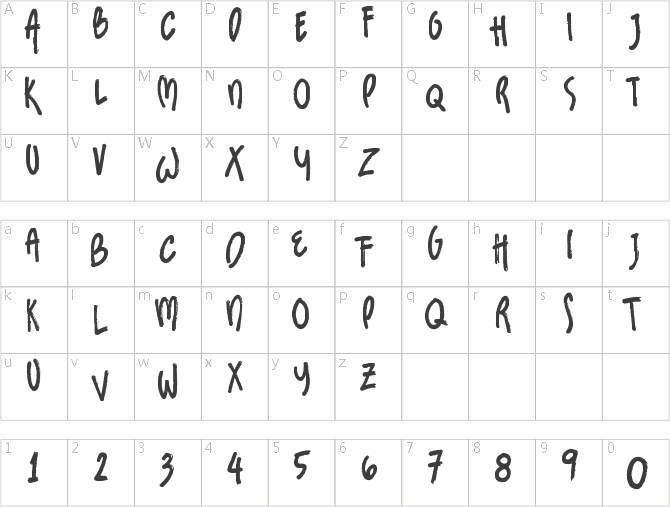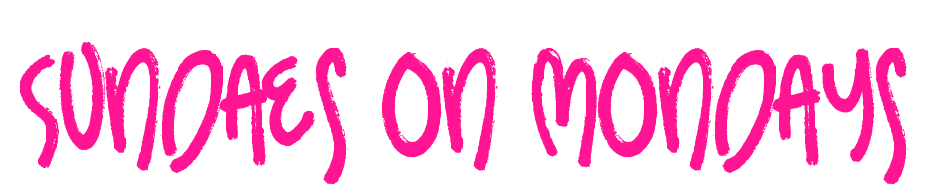
字體名稱: Sundaes
Sundaes on Mondays
Sundaes on Mondays字體字庫是一款讓人賞心悅目、百看不厭的英文字體,適合各類廣告和產(chǎn)品包裝設(shè)計應(yīng)用,字體大小0.1MB,格式為ttf字體,上傳用戶是星期一,作者/版權(quán)方為未知